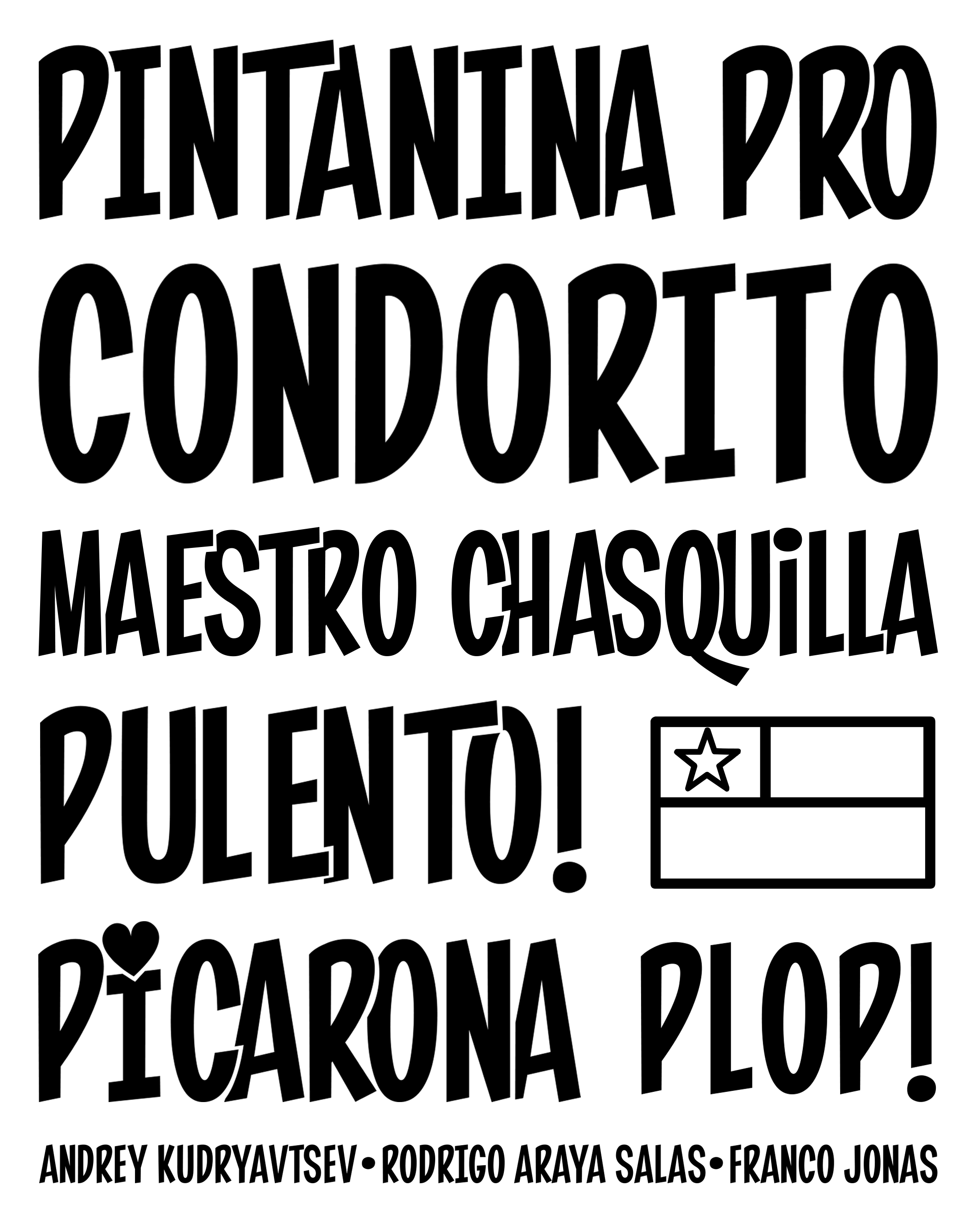
| Año | 2013 — Actualizada: ( 2017 ) |
| Créditos | Andrey Kudryavtsev, Rodrigo Araya Salas, Franco Jonas |
| Descripción | La familia tipográfica Pintanina Pro fue diseñada por Andrey Kudryavtsev, Rodrigo Araya Salas, Franco Jonas y publicada por RodrigoTypo. Pintanina Pro contiene 2 estilos y opciones de paquete familiar. Pintanina fue desarrollada en 2013 con muchas alternativas de alfabetos como ligaduras Basada en los Comics de Condorito en los titulares, una tipografía muy condensada dingbats que pueden ser de ayuda en los títulos. |
| Familia(s) | Pintanina Pro Regular |
| Estilos | 1 |
| Glifos | mayor que 1000 |
| Fundidora | RodrigoTypo |